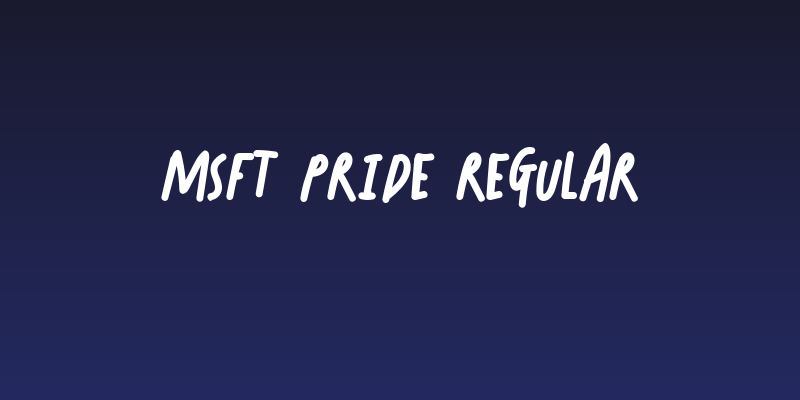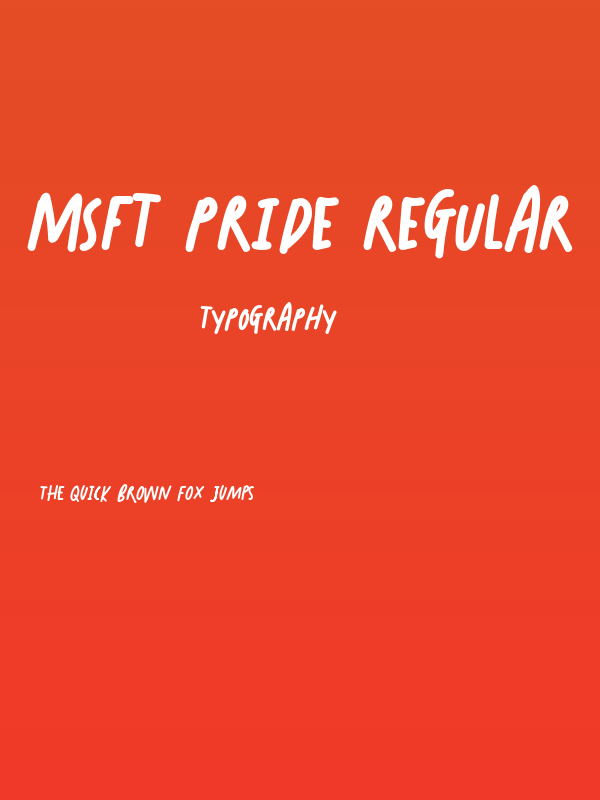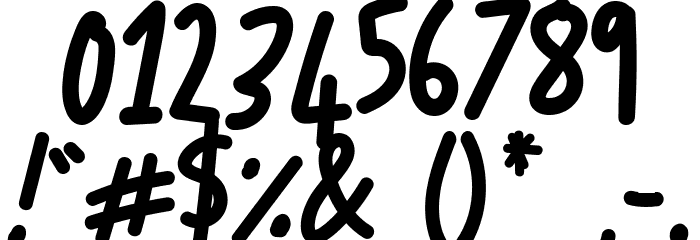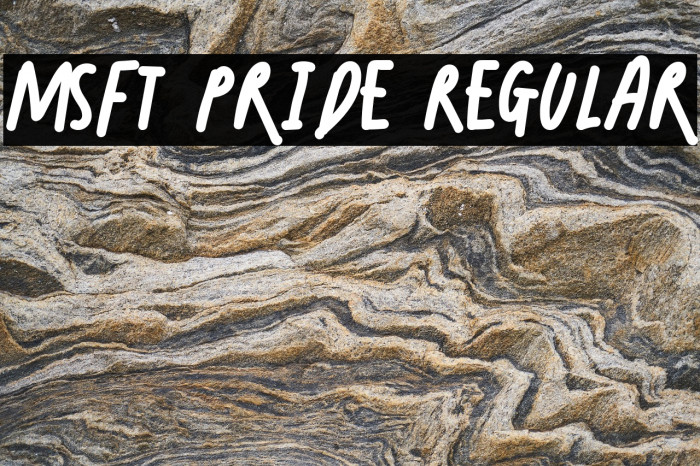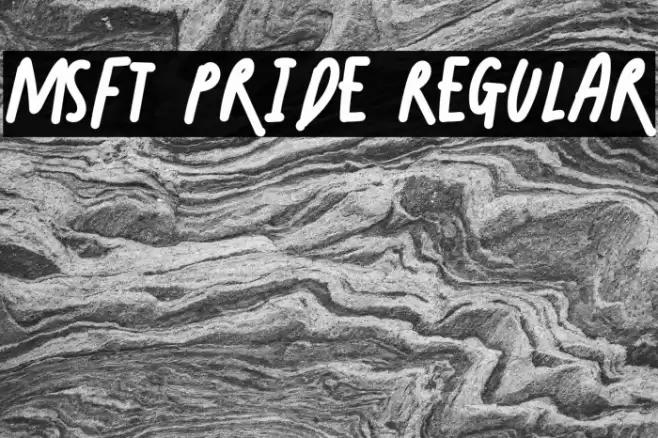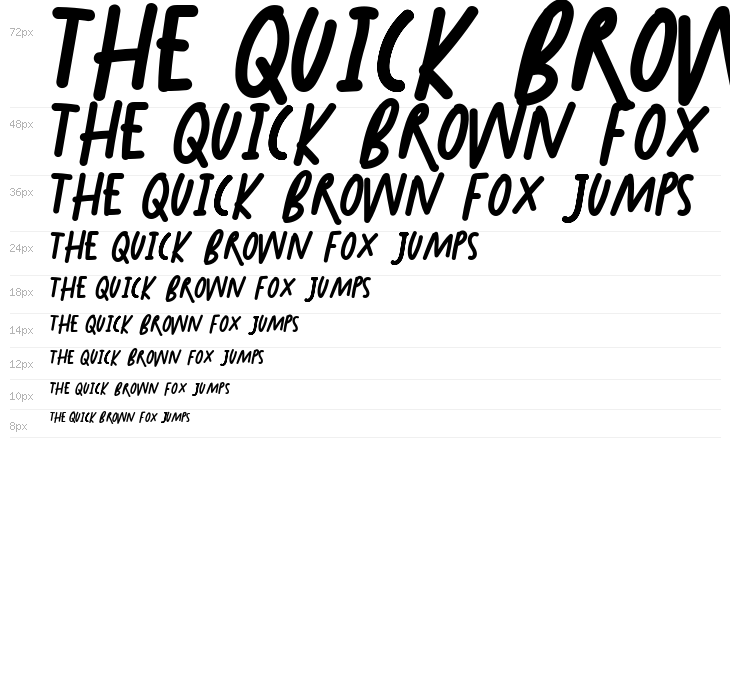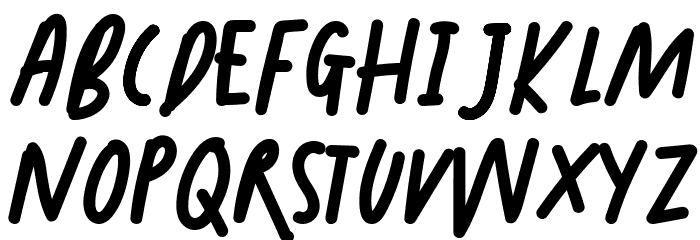
Msft Pride Regular Font
| النمط العام | Playful, Informal |
| حالة الاستخدام | Headlines, Logos, Informal Text |
| مشاريع مقترحة | Ideal for greeting cards, invitations, posters, and branding materials that seek a personal and informal touch. |